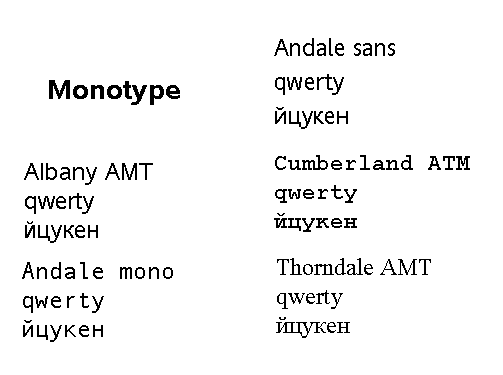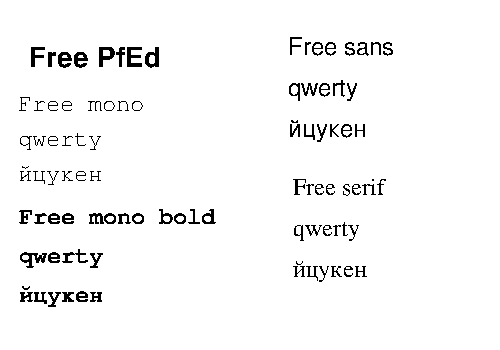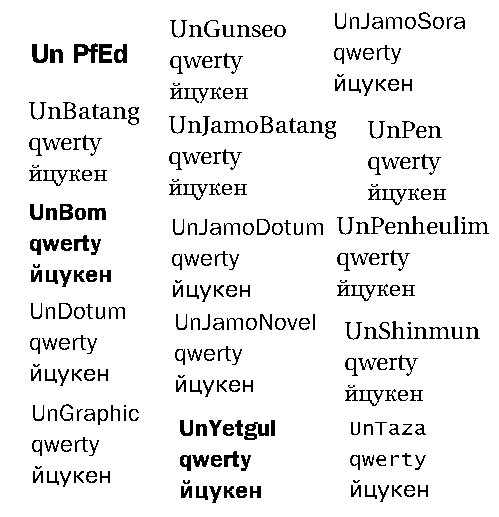
Шрифты для Иксов: полку TTF прибыло
Проблема шрифтов всегда остро стояла перед пользователями свободных операционных систем: создание шрифтов - дело хлопотное, и вполне можно понять желание их разработчиков получать за это деньги.
Особенно напряженно обстояло дело со шрифтами кириллическими. И если для консоли вопрос был практически решен с появлением пакета terminus-fonts (описанного здесь), то для Иксов до недавнего времени его разрешения как будто бы не предвиделось.
Нельзя сказать, что кириллических шрифтов для оконной системы X не было вообще. Нет, испокон веков в состав свободных их реализаций (XFree86 и в дальнейшем Xorg) входили кириллические шрифты для кодировки KOI8-R, разработанные на заре Рунета фирмой Cronyx. В дальнейшем они были усовершенствованы Дмитрием Болховитяновым, обретя заодно и поддержку всех кодировок великого и могучего. Однако и тот, и другой набор включал только растровые шрифты, и, соответственно, сфера их применения была ограниченной.
Были, конечно, и векторные шрифты. Первоначально Иксы сами по себе (без специального фонт-сервера) поддерживали только шрифты ATM. И в этом формате были созданы шрифтовые наборы Дмитрия Сорокина и Сергея Шарашкина. Однако они включали очень ограниченное количество гарнитур (а некоторые из шрифтов Сергея еще и были не вполне "чистыми" с лицензионной точки зрения).
Положение начало меняться только с появлением в Иксах поддержки шрифтов True Type. В этом формате Валентином Филипповым был создан первый самодостаточный и лицензионно безупречный шрифтовой набор, поддерживающий все кодировки кириллицы. Он же был продублирован и в формате ATM, что делает его в некоторых случаях незаменимым. Однако полностью потребности всех пользователей он удовлетворить не мог.
В результате наибольший успех в мире свободных операционок выпал, парадоксальным образом, на долю шрифтов от классового врага - Microsoft. Справедливости ради нужно заметить, правда, что шрифты эти суть достижение творческого гения фонт-дизайнеров фирмы Monotype, специализирующейся на такого рода деятельности, а Microsoft выступала только как заказчик и, в дальнейшем, собственник их.
Тем не менее, малый джентльменский набор ttf-шрифтов от Microsoft долгое время был свободно доступен с сайта этой фирмы. Не возбранялось и их относительно свободное распространение, на которое накладывалось три запрещения: на включение в состав каких-либо программ, на помещение на физические носители и на изменение формата архива (каковым был, понятное дело, микросфтовский cab).
То есть включать шрифты от MS в состав, например, дистрибутивов Linux (или в штатный комплект свободных Иксов) было нельзя. А единственным способом их легального использования оставалось скачивание с сайта фирмы (или каких-либо иных сайтов - запрета на распространение по Сети почему-то не было, даже после того, как сами шрифты на сайте Microsoft стали недоступны), преобразование cab-архива к какому-либо человеческому формату (для чего очень быстро придумали специальную утилиту - cabextaract) и установка в собственную систему руками.
Конечно, майнтайнеры дистрибутивов озаботились автоматизацией этого процесса, в результате чего в большинстве Linux- и BSD-систем появились пакеты под именем corefonts или подобным. Однако самих шрифтов они не содержали: это были просто сценарии для получения из Сети cab-архивов, их распаковки, записи в нужный каталог, создания служебных файлов (типа fonts.dir и fonts.scale) и, возможно, модификации конфигурационного файла Иксов. То есть все это дело напоминало несколько то занятие, которому вынуждены предаваться молодые люди, в силу каких-либо причин обделенные женским вниманием.
Конечно, пользователи так не поступали, имея в своем распоряжении более простой способ обзаведения микрософтовскими шрифтами, о котором мы скромно умолчим. Однако факт остается фактом: до последнего времени это был единственный легальный способ установки самодостаточного набора качественных ttf-шрифтов. Однако ныне у него есть не менее законная альтернатива: использование шрифтов из дистрибутива SuSE Linux версии 9.3.
Этот дистрибутив попал мне в руки во время неформального творческого семинара, проводившегося сотрудниками фирмы Novell, и был почти немедленно установлен. Останавливаться на самом дистрибутиве я не буду - это тема отдельного разговора. Скажу только, что сразу после инсталляции мое внимание привлек каталог /usr/X11R6/lib/X11/fonts/TTF. Который содержал просто немерянное количество True Type шрифтов, большинство названий которых были мне незнакомы, а качество местами просто впечатляло. И, что было особенно интересно, каталог этот содержал не что иное, как текст лицензии GPL. Из чего следовал резонный вывод, что все его содержимое подлежит свободному распространению.
Внимательный просмотр содержимого каталога показал, что в нем собраны шрифты разного происхождения. Во-первых, здесь обнаружились работы известного фонт-дизайнера Рэя Лараби. Правда, для наших целей они не очень интересны - так как носят преимущественно декоративный характер (да и, между нами говоря, кириллицу не поддерживают).
Было там и большое количество каких-то изначально свободных (судя по частичке Free в описаниях) шрифтов неизвестного мне происхождения - как поддерживающих кириллицу, так и игнорирующих ее.
И, наконец, самое главное: шрифты производства фирмы Monotype, той самой, что разработала corefonts для Microsoft. И эти шрифты сработаны столь же аккуратно и качественно. Правда, представлены они лишь четырьмя гарнитурами - двумя серифами (Cumberland и Thorndale) и двумя шрифтами без отсечек (Albany и Andale Sans). Но зато поддерживают кириллицу во всех ее проявлениях - от Unicode до бомжовской KOI8-R. А уж о качестве шрифтов и говорить не приходится...
Впрочем, в отношении качества - лучше один раз увидеть, чем сто раз услышать. А увидеть можно на рисунке 1.
Если все же покажется, что шрифтов от Monotype мало - есть смысл пройтись по тем свободным шрифтам, о которых я упоминал выше. Среди них можно подобрать также очень неплохие. Что и иллюстрируется рисунками 2 и 3.
Впрочем, в отношении шрифтов лучше даже не увидеть, а попробовать. Для чего достаточно их скачать здесь - в этой коллекции собрано все кириллическое, что я выудил из ttf-каталога дистрибутива SuSE 9.3.